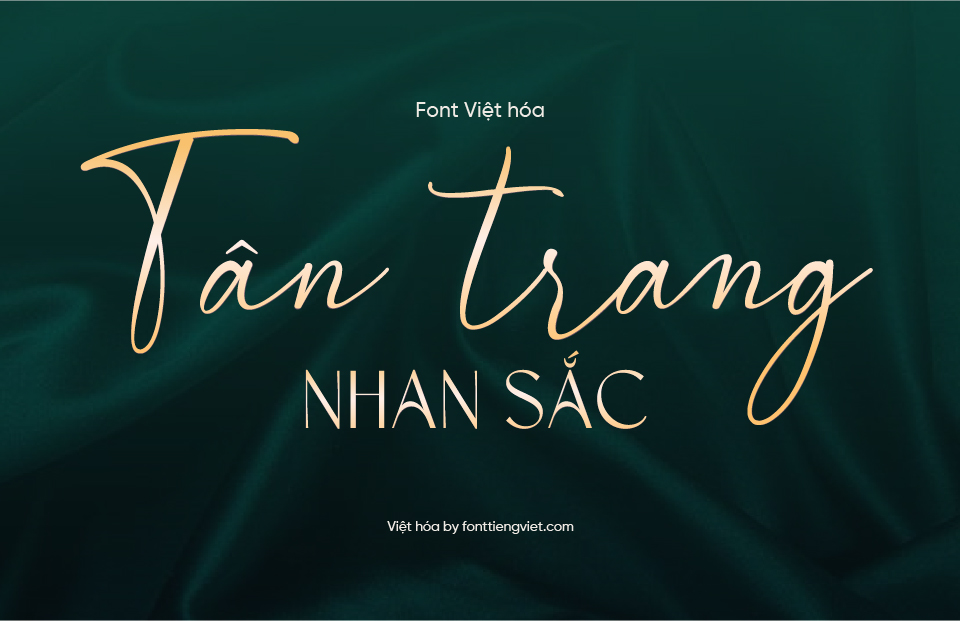
Font Việt hóa 1FTV VIP Southland
Trong thế giới thiết kế đồ họa hiện đại, việc lựa chọn một bộ Font Miễn Phí chất lượng luôn là ưu tiên hàng đầu của các designer chuyên nghiệp. Font Việt hóa 1FTV VIP Southland nổi lên như một sự lựa chọn hoàn hảo nhờ phong cách phóng khoáng và hiện đại. Đây là bộ font script được tinh chỉnh kỹ lưỡng về dấu câu tiếng Việt, giúp người dùng dễ dàng ứng dụng vào nhiều loại hình dự án khác nhau từ học đường đến nghệ thuật mà không lo lỗi hiển thị.
Đặc điểm nổi bật của Font Việt hóa 1FTV VIP Southland
Phong cách thiết kế chữ viết tay sáng tạo
Font Việt hóa 1FTV VIP Southland sở hữu những đường nét thanh mảnh nhưng vô cùng dứt khoát, mô phỏng chân thực kiểu chữ viết tay đầy cá tính. Các nét nối giữa những ký tự được xử lý mượt mà, tạo nên cảm giác uyển chuyển và tự nhiên cho văn bản. Điều này giúp bộ font trở nên cực kỳ phù hợp cho các thiết kế thiệp mời, bìa sách giáo khoa hoặc các ấn phẩm truyền thông dành cho giới trẻ hiện nay.
Khả năng tương thích và ứng dụng đa dạng
Bộ font này đã được tối ưu hóa hoàn toàn để sử dụng trên các phần mềm đồ họa phổ biến như Photoshop, Illustrator hay Canva. Nhờ bảng mã chuẩn, bạn có thể gõ tiếng Việt một cách trơn tru mà không gặp bất kỳ trở ngại nào. Với Font Việt hóa 1FTV VIP Southland, các bạn học sinh và sinh viên có thể tự do sáng tạo những bài thuyết trình ấn tượng hoặc trang trí sổ tay điện tử thêm phần sinh động và bắt mắt.
Cách sử dụng Font Việt hóa 1FTV VIP Southland hiệu quả
Để tận dụng tối đa vẻ đẹp của bộ chữ này, bạn nên kết hợp nó với các font chữ không chân (sans-serif) đơn giản nhằm tạo ra sự tương phản tinh tế. Đừng quên điều chỉnh khoảng cách dòng và kích thước chữ sao cho phù hợp với bố cục tổng thể. Việc sở hữu một bộ font đẹp như 1FTV VIP Southland sẽ nâng tầm giá trị thẩm mỹ cho mọi tác phẩm sáng tạo của bạn.
Kết luận về bộ font Southland việt hóa